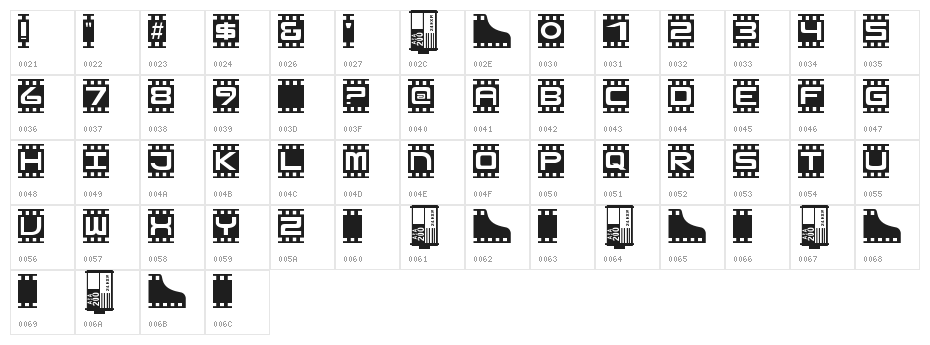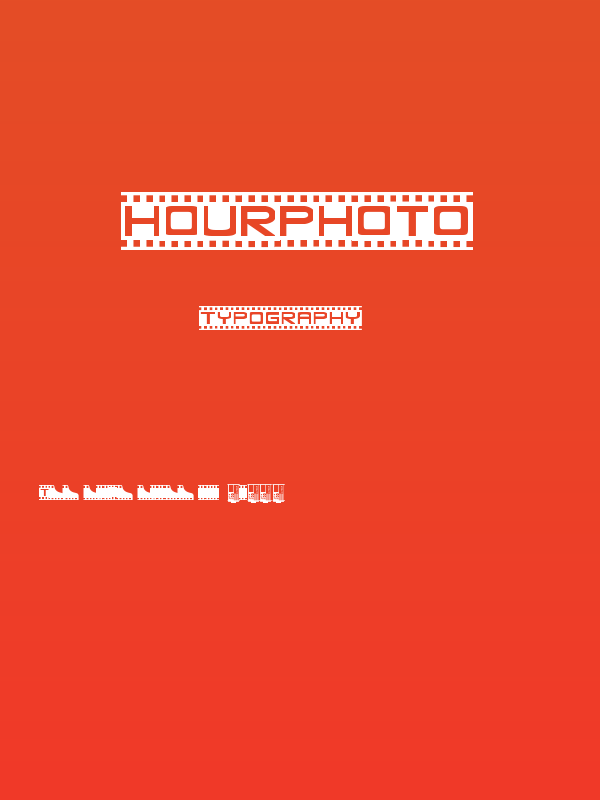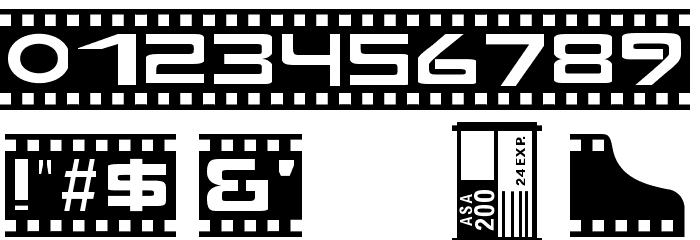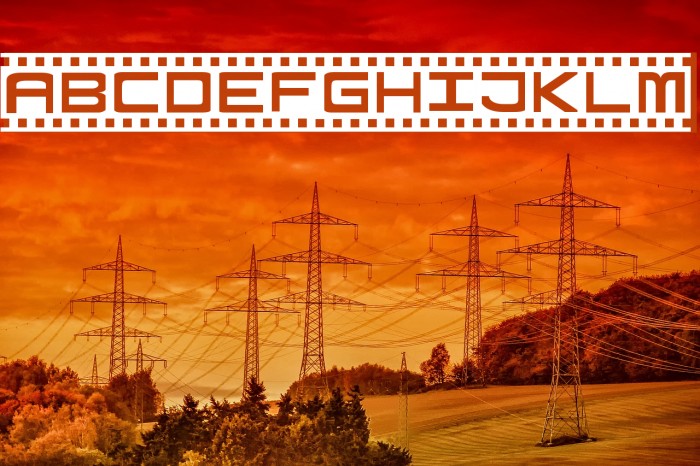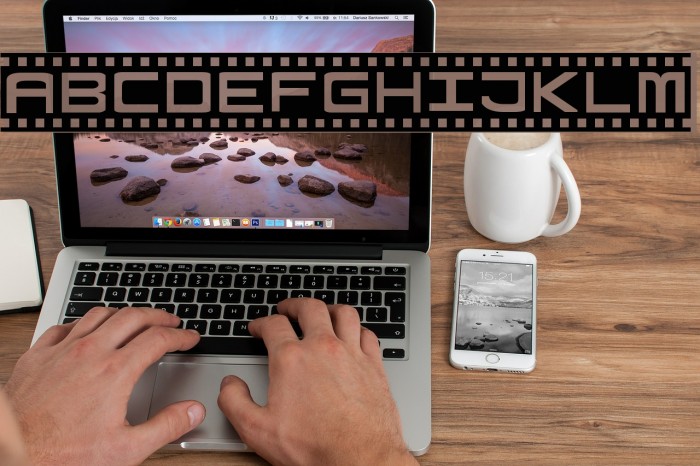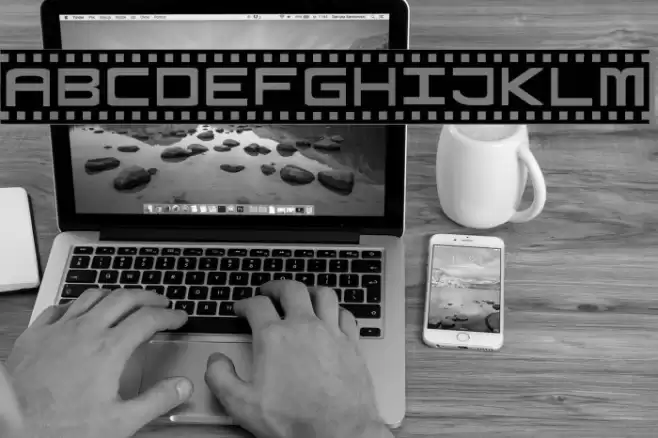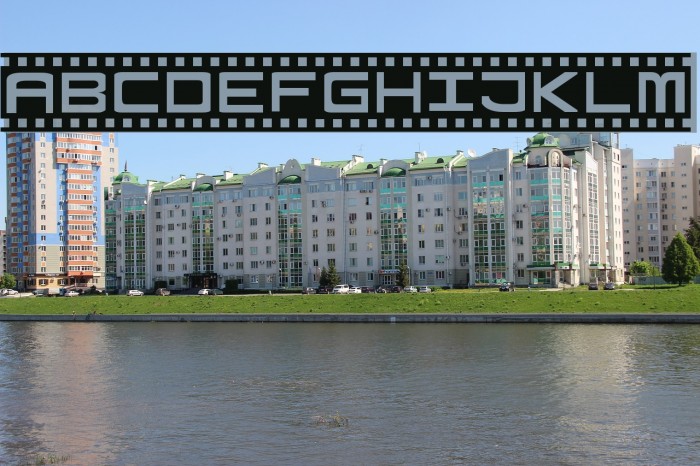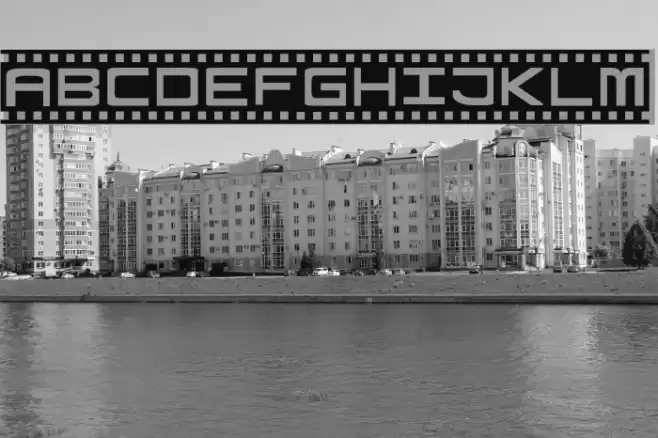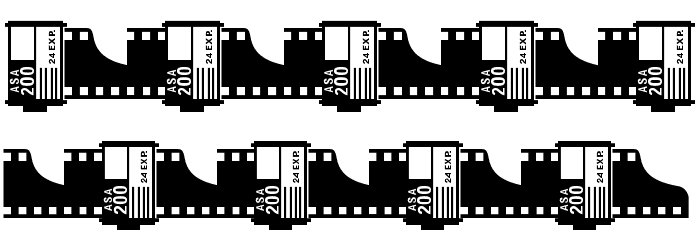
HourPhoto Font
| Vorgeschlagene Projekte | Ideal for movie posters, photography blogs, retro-themed designs, and any project seeking a cinematic or nostalgic aesthetic. |